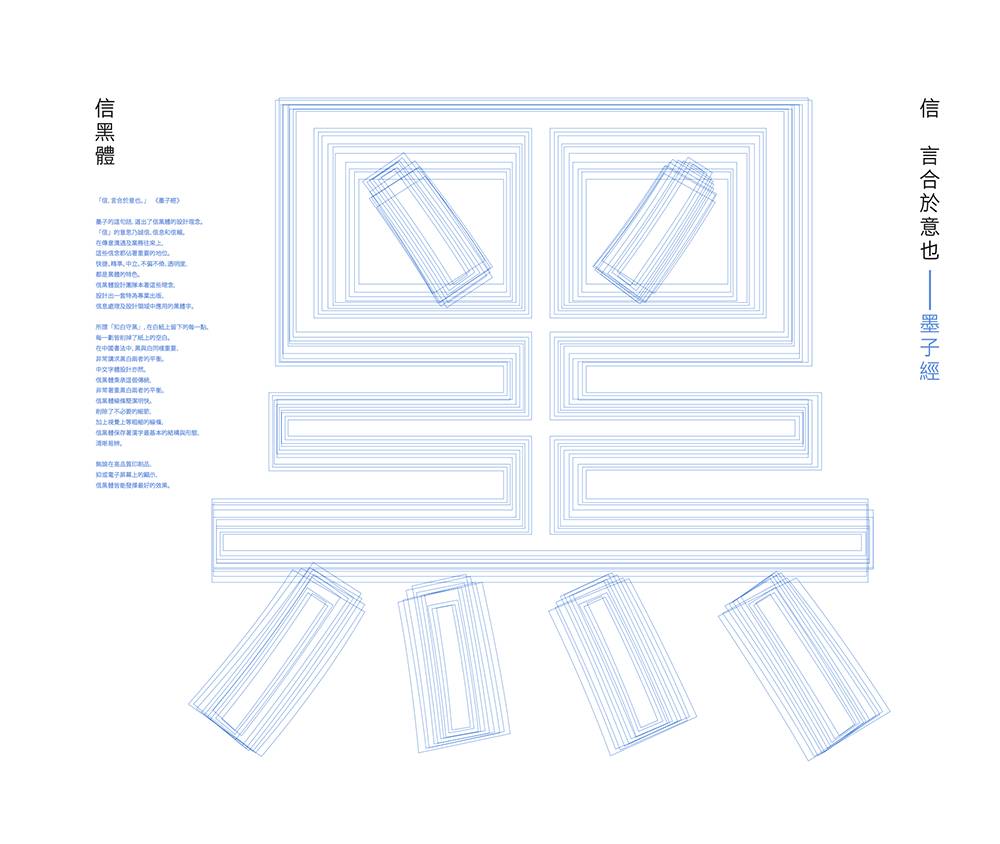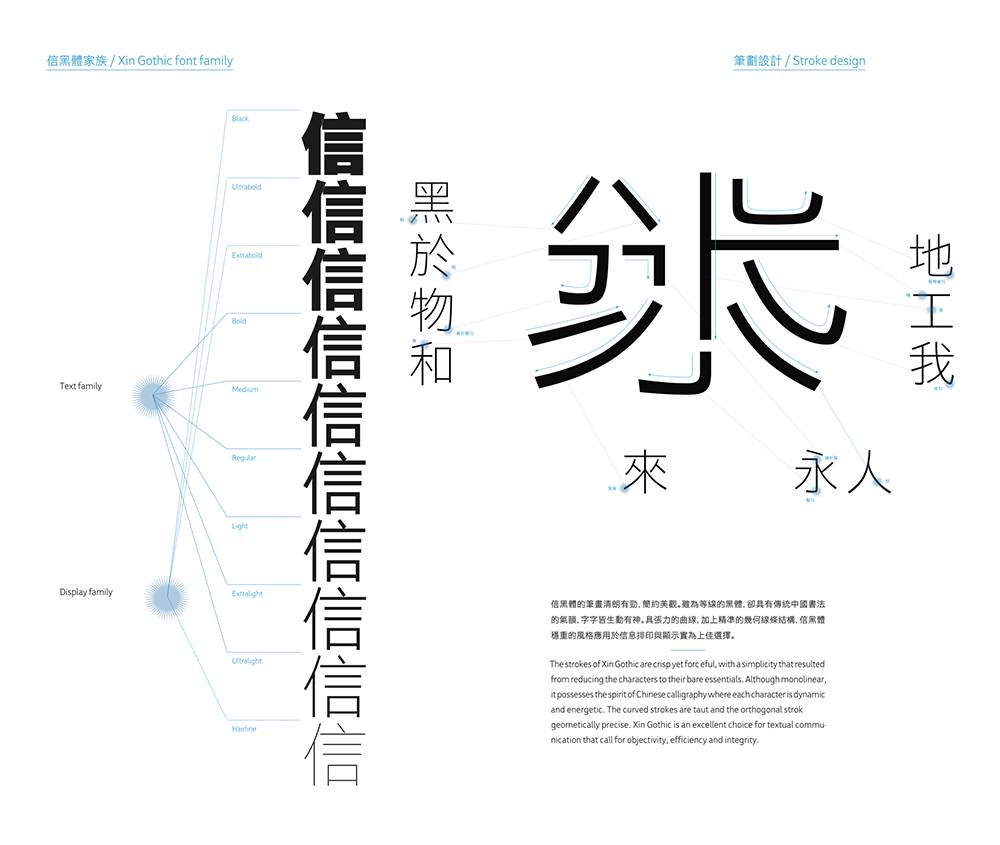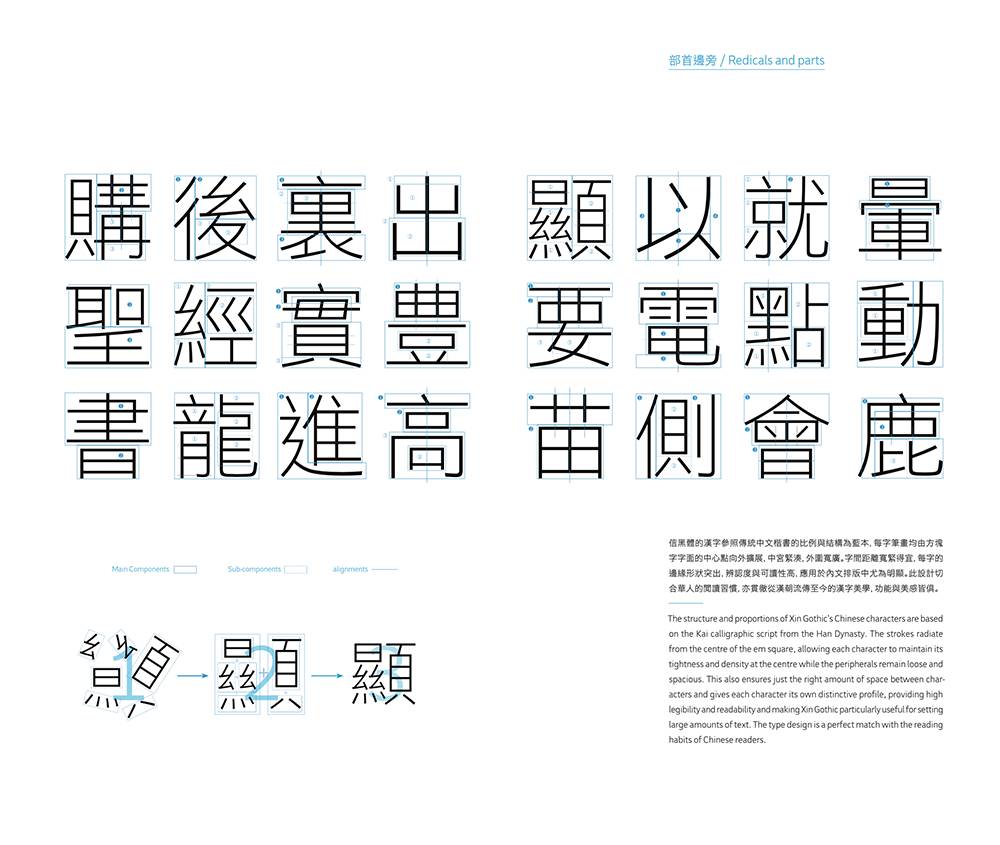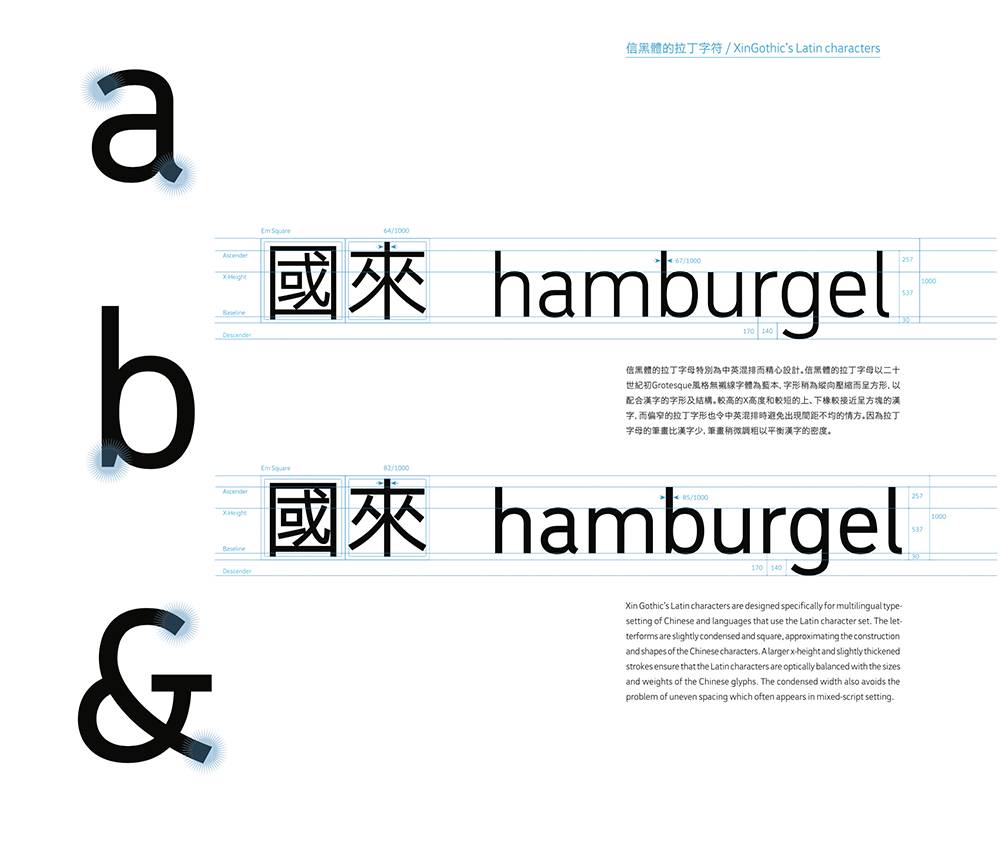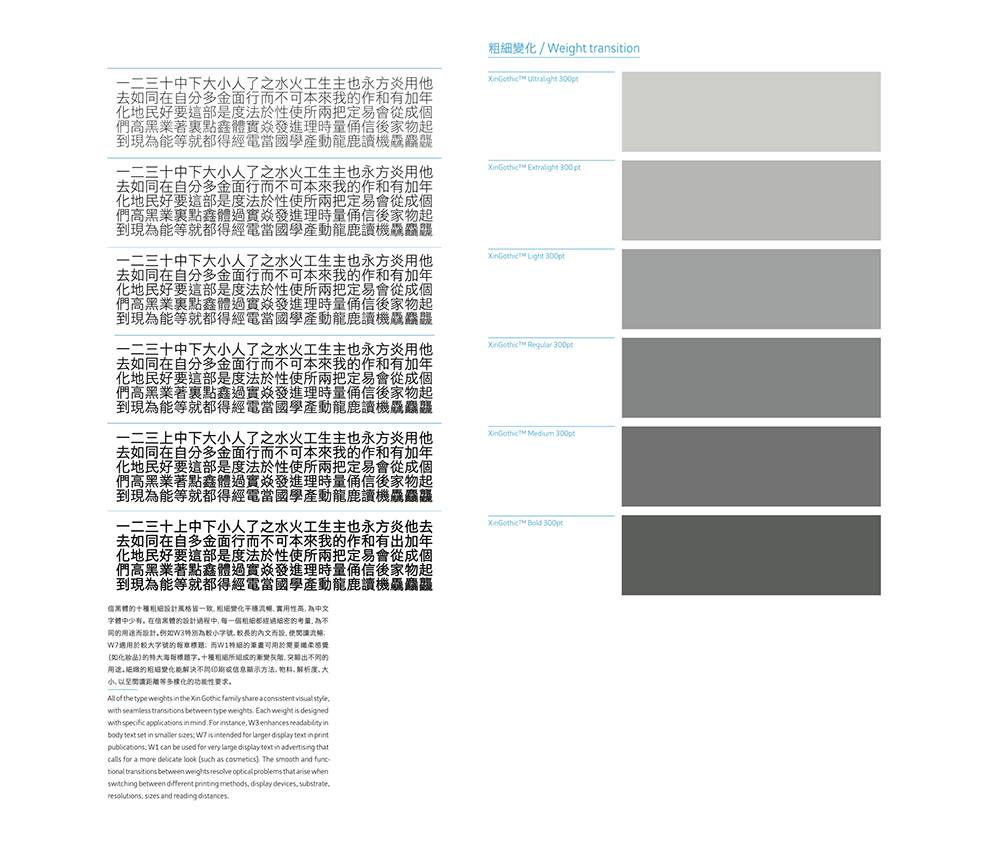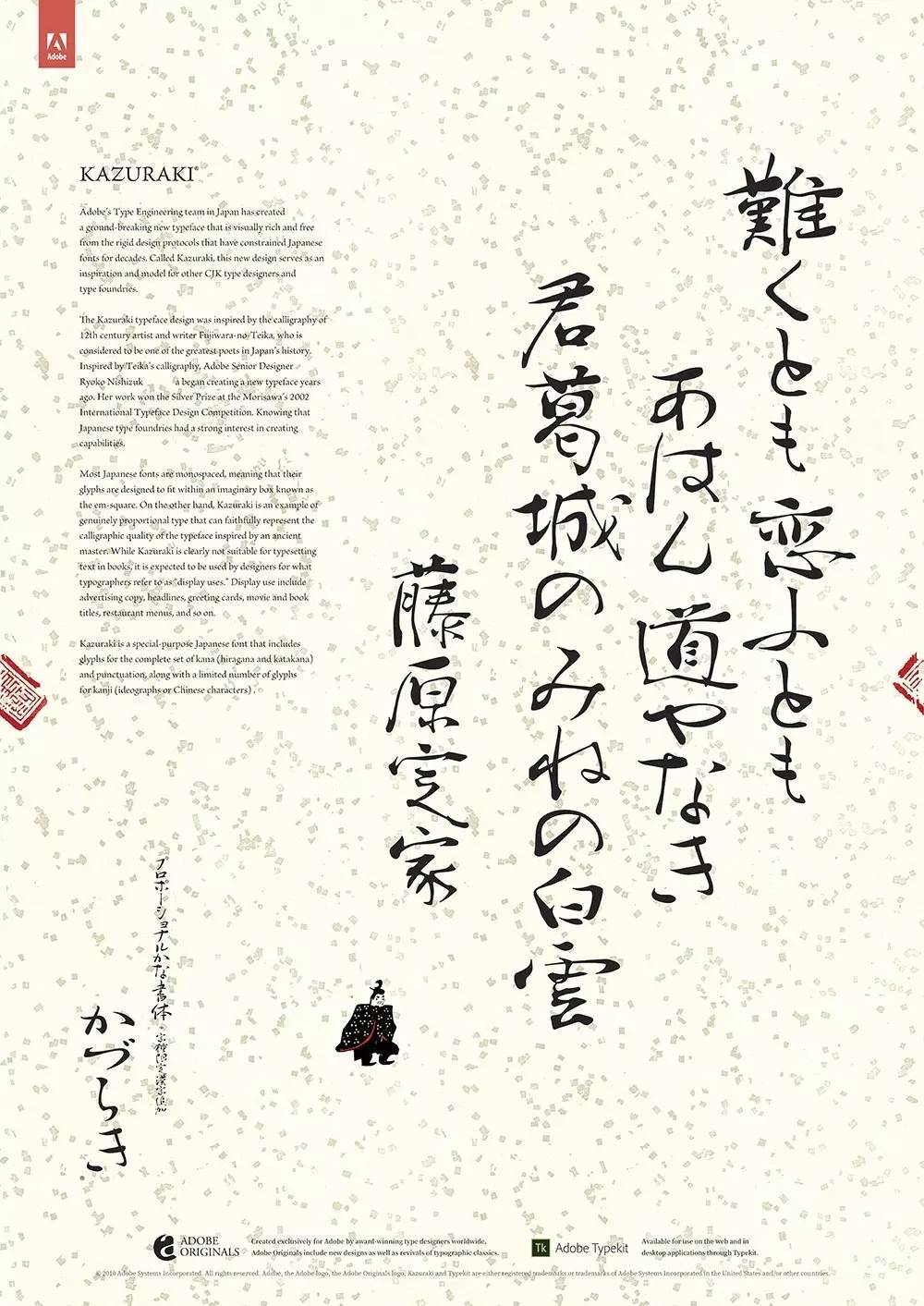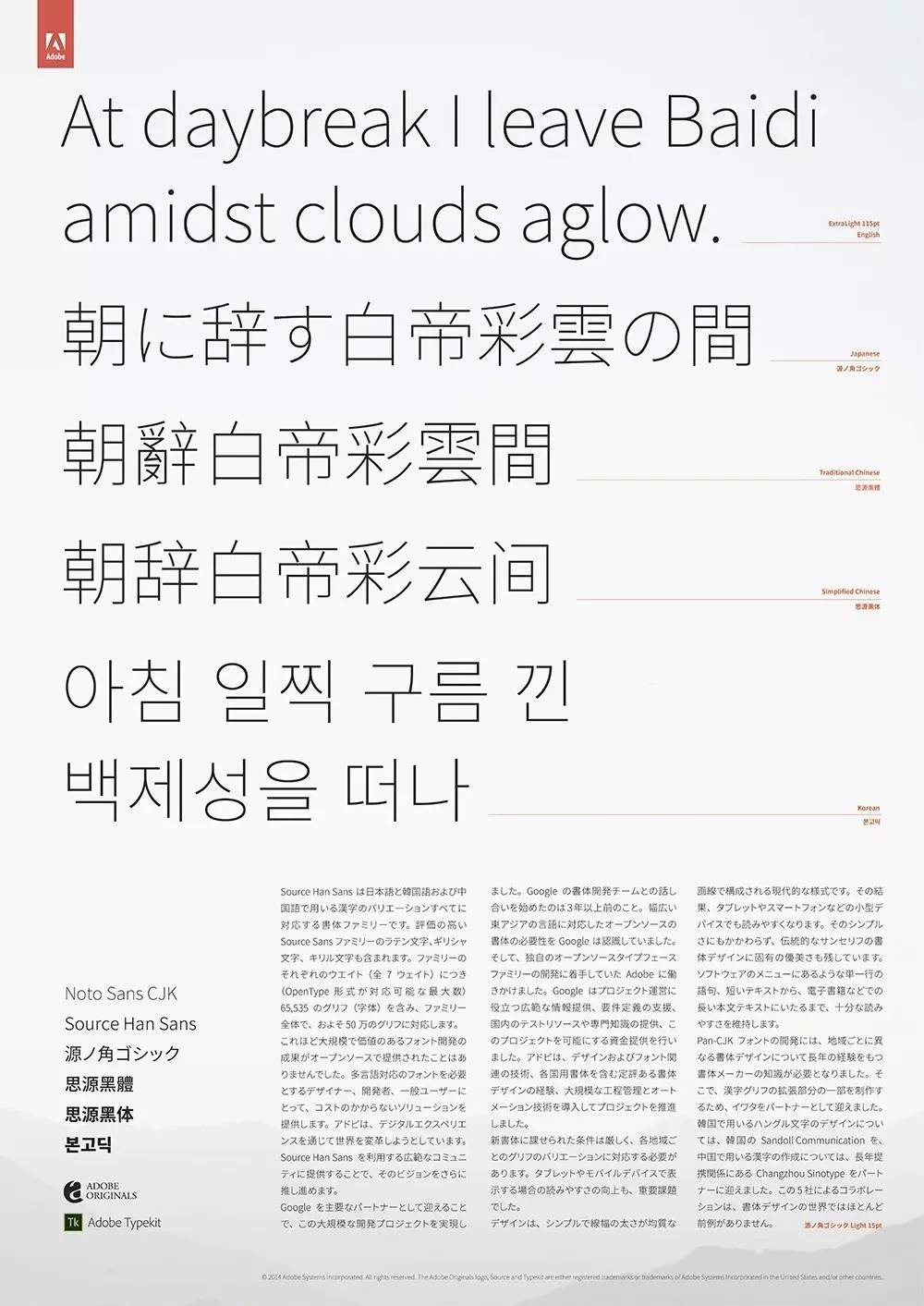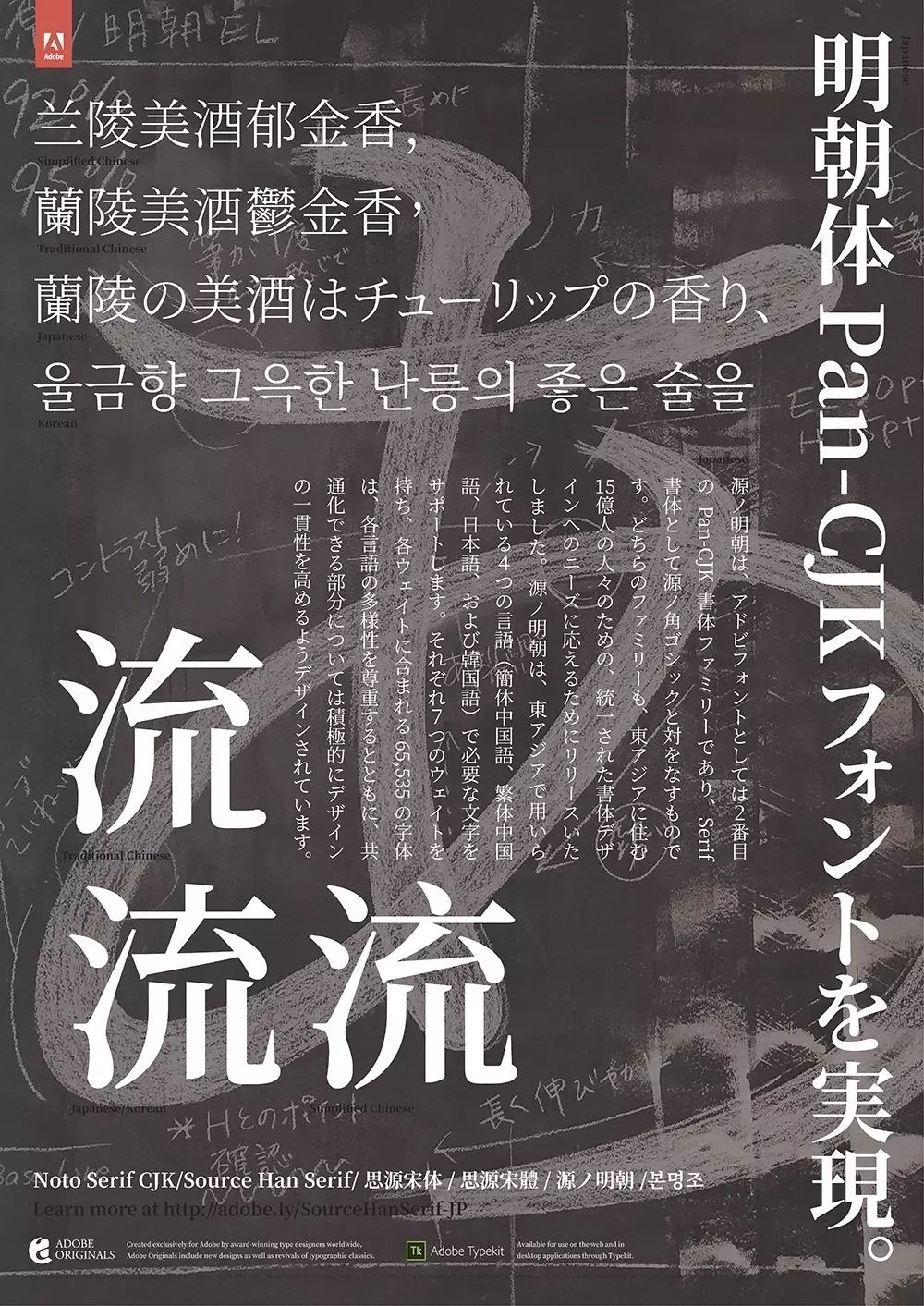
GDC17丨字体设计国际评审团分享:你每天都用的字体是他们设计的
GDC(Graphic Design in China)平面设计在中国展是中国首个面向全球的大型综合性设计竞赛双年展活动,每两年举办一次,由深圳市平面设计协会(SGDA)创办自1992年。这一设计竞赛活动已经成为华人地区影响最大、水平最高、且最具权威和公正性的设计盛典。
GDC竞赛汇集全球顶尖设计师和新生力量的最新设计成果,以“影响中国未来的设计”为宗旨,其评审结果将更为直接地体现出当下设计与文化、商业、生活的互动关系,为中国未来的设计建立全新的价值标准。
超级阵容
全球设计精英联袂坐镇评审
15位国际知名设计师组成的评审团,将对参赛作品进行现场评比。基于本届GDC策展方向,我们针对性的邀请了不同语种、不同文化背景及专业方向的顶尖设计师,他们分别在各自领域取得了卓越成就。
GDC17设计竞赛评审团将着重围绕“视觉传达、时代主张、信息介质、多维呈现”四个核心关键词,对参赛作品给予甄别与褒奖,以期深入探讨新时期平面设计的演进方向,在一个更宏观的视域内,建立全新的设计价值标准。
——
文字设计:从学术课题到全民语境
——
一个不争的事实是,在平面设计领域,字体设计正在作为一个准独立板块异军突起,在今天,如果一个平面设计师都没有深度接触过字体设计的话,这将会是一件很不正常的事。
今年4月,SGDA举办了首届China TDC  文字设计在中国系列活动,受到空前广泛的关注。越来越多的字体设计师群体从后平台来到前台,文字设计的影响力正从专业领域扩展到更广阔的社会生活与日常语境,文字设计话题达到一个前所未有的活跃度。
作为中国最重要的设计竞赛活动,历届GDC参赛作品中亦不断涌现大量优秀的文字设计作品,本届GDC,我们决定于平面设计类别中增设文字设计组,同时邀请到三位具有国际性影响力的字体设计师担纲评审,以期甄选并展示当代最具专业度与探索力的文字设计师,为不断增强的中国字体设计力量提供价值参考标准。
GDC17
平面视觉类文字设计组国际评审团
西塚凉子 × 刘永清 × 柯炽坚
————————————————
西塚凉子
Ryoko Nishizuka
(日本 JPN)
任职Adobe systems研究开发总部
资深日语字体设计师
1972年,于日本福岛县出生。1995年,毕业于武藏野美术大学造型学部视觉传达设计专业。1997年,进入Adobe Systems,师从小塚昌彦,并曾经参与“小塚明朝”、“小塚黑体”的开发。
此后,设计了Adobe原创的日语假名字体“りょう’ 及‘りょう黑体”  系列,以及全比例字体“かづらき”、“思源黑体”、“思源宋体”。曾获奖项有日本森泽国际字体大赛、NY TDC评审奖等。
Kazuraki_poster
Sourece Han Sans_poster
Sourece Han Serif_poster
————————————
刘永清
Liu Yongqing
(中国 CHN)
深圳市平面设计协会(SGDA)第七届理事会 主席
华思品牌营销设计机构 创始人
华思品牌营销设计机构创始人,曾任深圳市平面设计协会主席,广州美术学院研究生课程导师及多所院校客座教授,十大年度创意人物、意大利全球最佳品牌设计大奖赛评委,中国品牌年鉴编委、方正字库特邀字体设计师、为三百多家企业做过品牌形象整合设计服务,其中上市公司52家,作品多次在国内外设计大赛中获奖并被收藏。
获奖经历
日本Good Design创新设计大奖
金点国际设计奖最高荣誉奖
东京TDC字体指导俱乐部全球年度设计提名奖
意大利全球年度形象设计文化类最佳设计大奖
首届中国设计大展平面类最佳设计大奖
GDC11/13连续两届最佳设计大奖及协会奖
HKDA13环球设计大赛银奖两项、铜奖等多项
七彩设计奖视觉类大奖
HKDA11香港环球设计大赛银奖两项、铜奖两项
IDE国际品牌形象设计大赛全场大奖
第11/12届全国美展提名奖、进京奖
中国品牌设计年鉴金奖等多件
第五届国际商标标志双年奖银奖等多件
GDC07设计双年展银奖及铜奖等200余项
其作品多次在德国、美国、英国、澳大利亚、俄罗斯、巴塞罗那、韩国、日本、华沙、香港、台湾、北京、深圳、上海、广州等海内外展出。
风雅楷宋
华思字体实验
江南意象
现代中国
GDC13-易
————————————
柯炽坚
Sammy Or
(中国香港 HK CHN)
资深中文字体设计师
域思玛字体设计公司 总裁及首席字体设计师
柯炽坚老师拥有三十年经验,是一位的资深中文字体设计师。其中文字体作品为数不少,为当代中文字体设计界的翘楚。柯老师对传统中国书法有相当的研究,加上对现代字体科技的深入暸解,所设计的字体广为各华文媒体采用。
柯老师于一九八零年代加入香港地下铁路公司,担任导向指示系统设计师一职。其参与设计的地铁宋体特别为导向指示系统设计,现在仍然使用中。其后柯老师转职至蒙纳中国字体设计公司,出任字体经理兼首席字体设计师。任职蒙纳的时期,柯老师设计了二十多款字体,包括最早期推出,为香港政府印务局设计的中文镭射排版字体。其中广泛于香港地区被采用的蒙纳宋体及黑体亦出自柯老师的手笔。香港特别行政区政府、牛津大学出版社圴选用蒙纳宋、黑体为标准用字。
一九八九年, 柯炽坚创立TTL字体科技有限公司,锐意研发中文向量外框字体。俪宋、俪黑体为首两个中文外框字体,特别为苹果电脑的中文系统设计,现在每一部苹果出产的 电脑仍然附带俪宋和俪黑体于其作业系统中。一九九二年,柯老师应台湾华康之邀,担纲副总裁兼首席字体设计师之要职。在华康科技时,柯老师设计了多种新中文字体,包括大受好评的瘦金体,和逾三十款字体的“俪”系列。在柯老师的领导下,华康科技的业务亦扩展至上海和日本。柯炽坚亦为著名美国Bitstream字体科技公司担任中、日韩文的字体设计顾问达十年之久。 二〇〇八年,柯炽坚创立域思玛字体设计公司,现任职总裁及首席字体设计师。柯老师曾任敎于台湾内实践学助理副教授,亦为香港理工大学设计学院客席讲师。
1972~1976 李奥贝纳 广告公司 设计师
1977~1980 香港地下铁指标系统设计师
1982~1986 蒙纳 (Monotype Hong Kong) 经理兼首席字体设计师
1987~1991 创立 Type Technology Limited 开发俪宋,俪黑, 俪字体系列
1992~1998 台湾华康 副总裁兼首席字体设计总监
1999~2002 美国 Bitstream 中文字体顾问
2008~2017 创立 域思玛 (Visionmark Ltd,) 字体设计 开发信黑体系列
xin gothic specimen edited